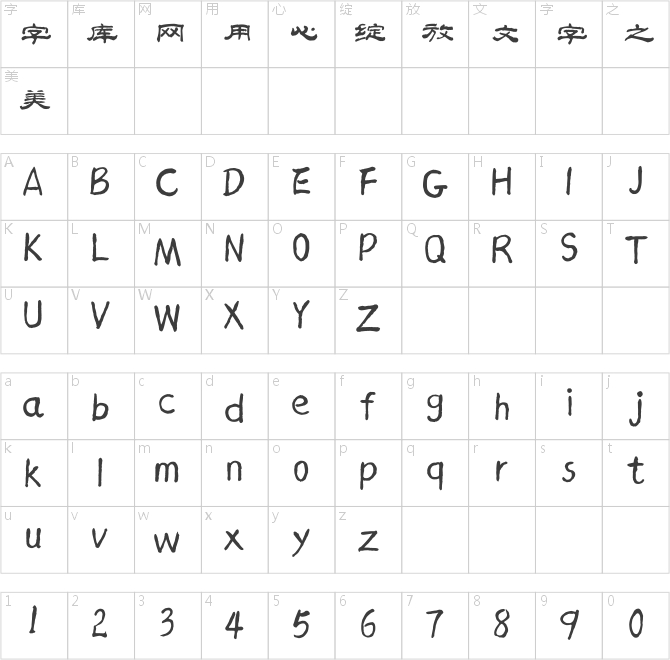
漢標(biāo)叢臺(tái)體
漢標(biāo)叢臺(tái)體字體字庫是一款讓人賞心悅目、百看不厭的中文字體,適合各類廣告和產(chǎn)品包裝設(shè)計(jì)應(yīng)用,字體大小3.61MB,格式為ttf字體,上傳用戶是漢標(biāo)文創(chuàng),作者/版權(quán)方為漢標(biāo)字庫